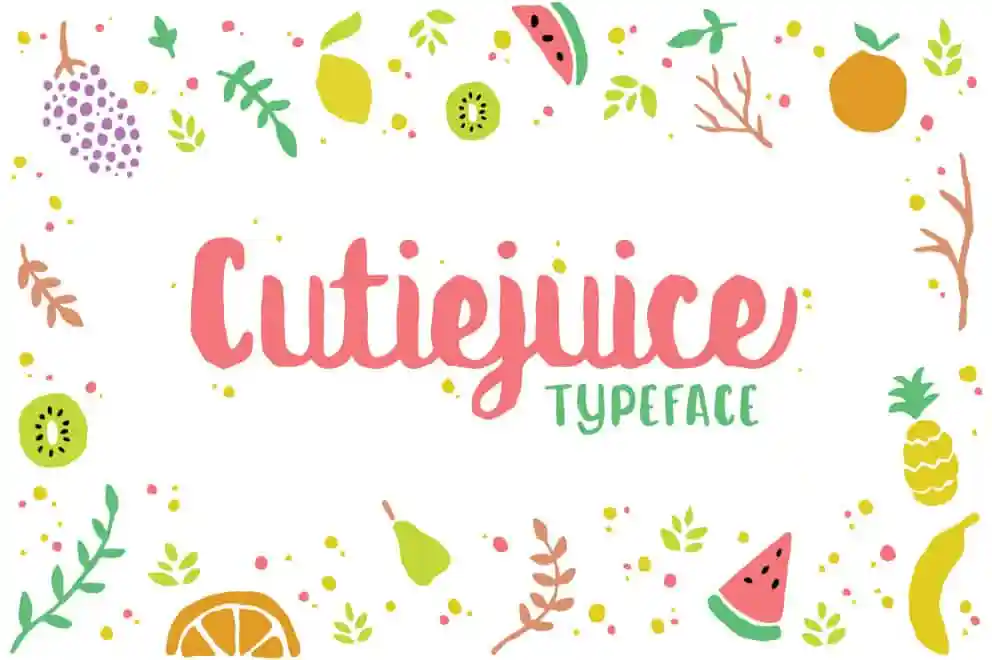
Cutiejuice Script Font – Download Grátis
A Cutiejuice é uma tipografia cheia de vitaminas, perfeita para qualquer trabalho divertido e quirk. É um tipo script adorável ideal para quem busca dar vida aos seus projetos com charme feminino. Este tipo se encaixa tão bem em ambientes limpos e modernos serifados ou san-serifados como pode ver nas imagens acima, que também brilha por si só! Sempre pronta para adicionar um toque de encanto a qualquer design sem necessidade de complemento exagerado.